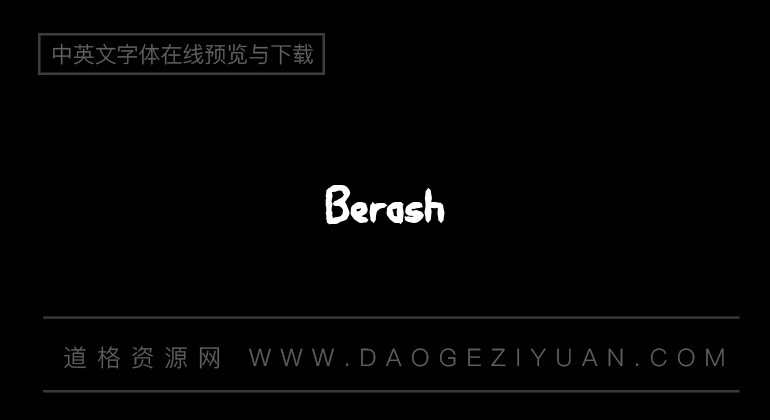
Berash 是一款开源字体,由设计师 Alexey Kryukov 设计。该字体最初是为卡累利阿语设计的,但是也可以用于其他语言。Berash 字体具有紧凑的外观和清晰的线条,可以显示各种字形,并且在小字体大小下非常清晰易读。此外,Berash 字体还具有多种字重,从普通的正常字重到黑体和粗体字重。Berash 字体适用于数字设备和打印媒体,并且可以用于各种用途,例如标题、段落文本、标签、按钮等。内容介绍
Berash是一款非常不错的手写艺术字体,具有很好的视觉感,适合于文化类的宣传设计、商业类品牌的广告和产品包装设计以及个性化文字排版等较多场景。